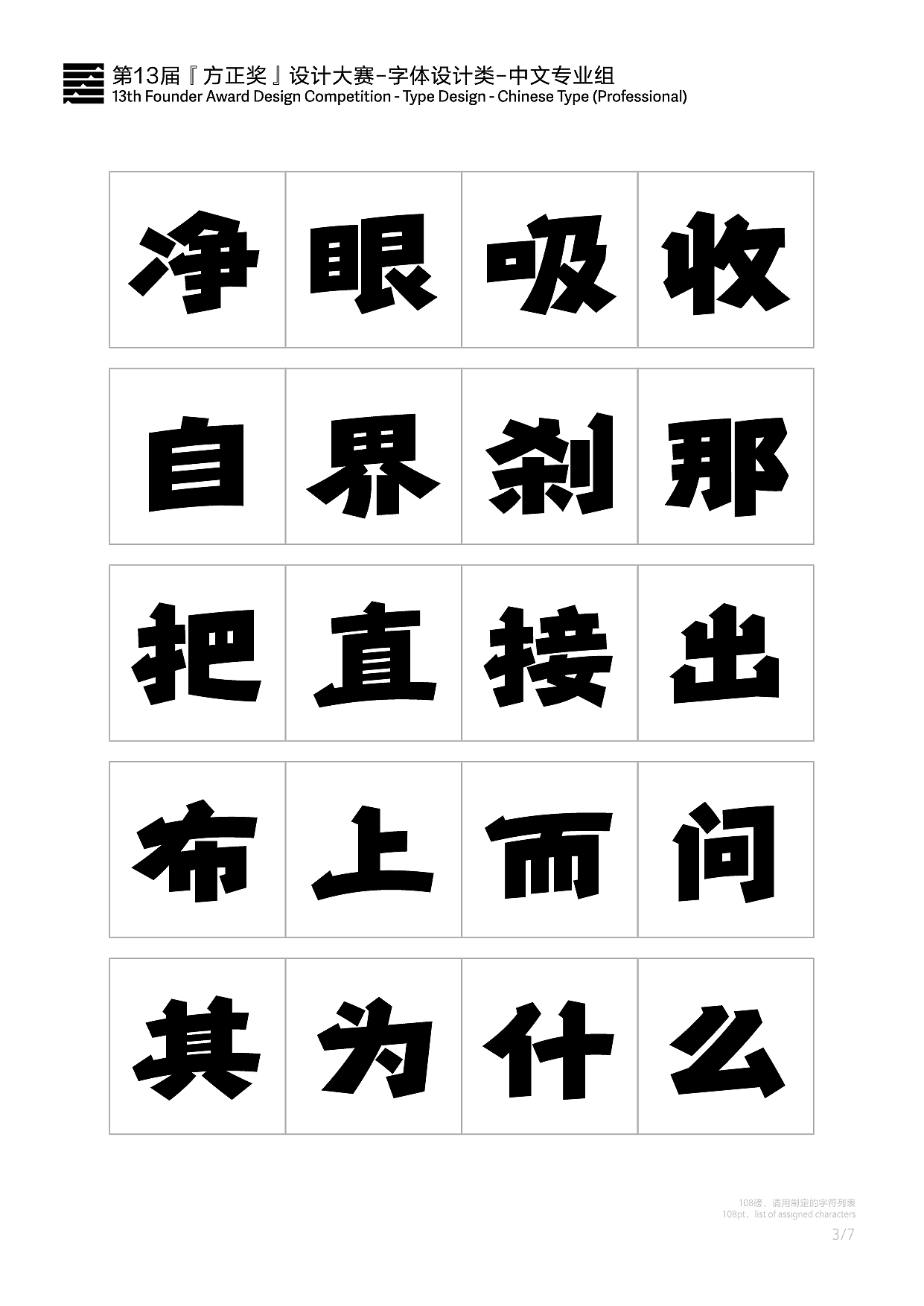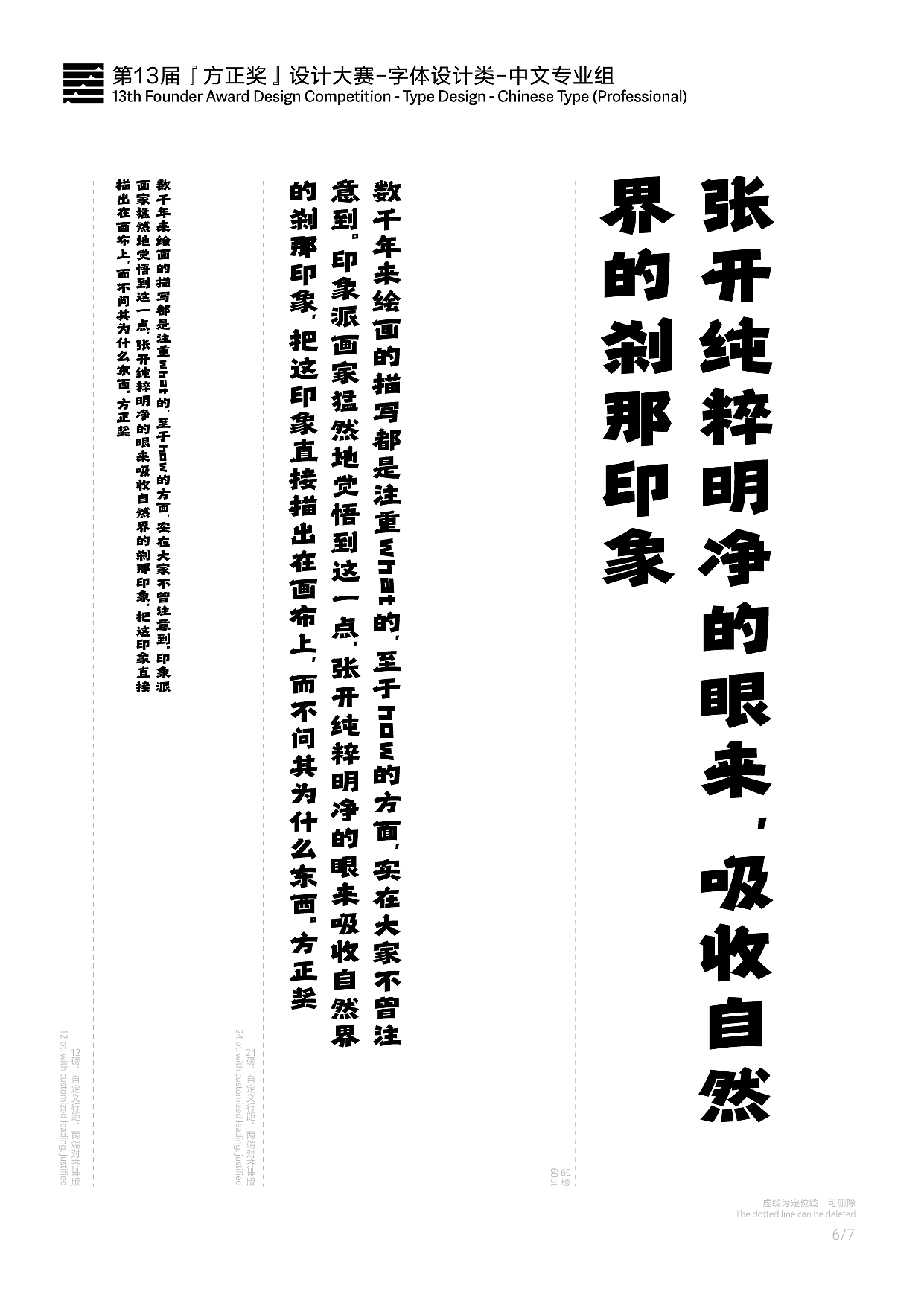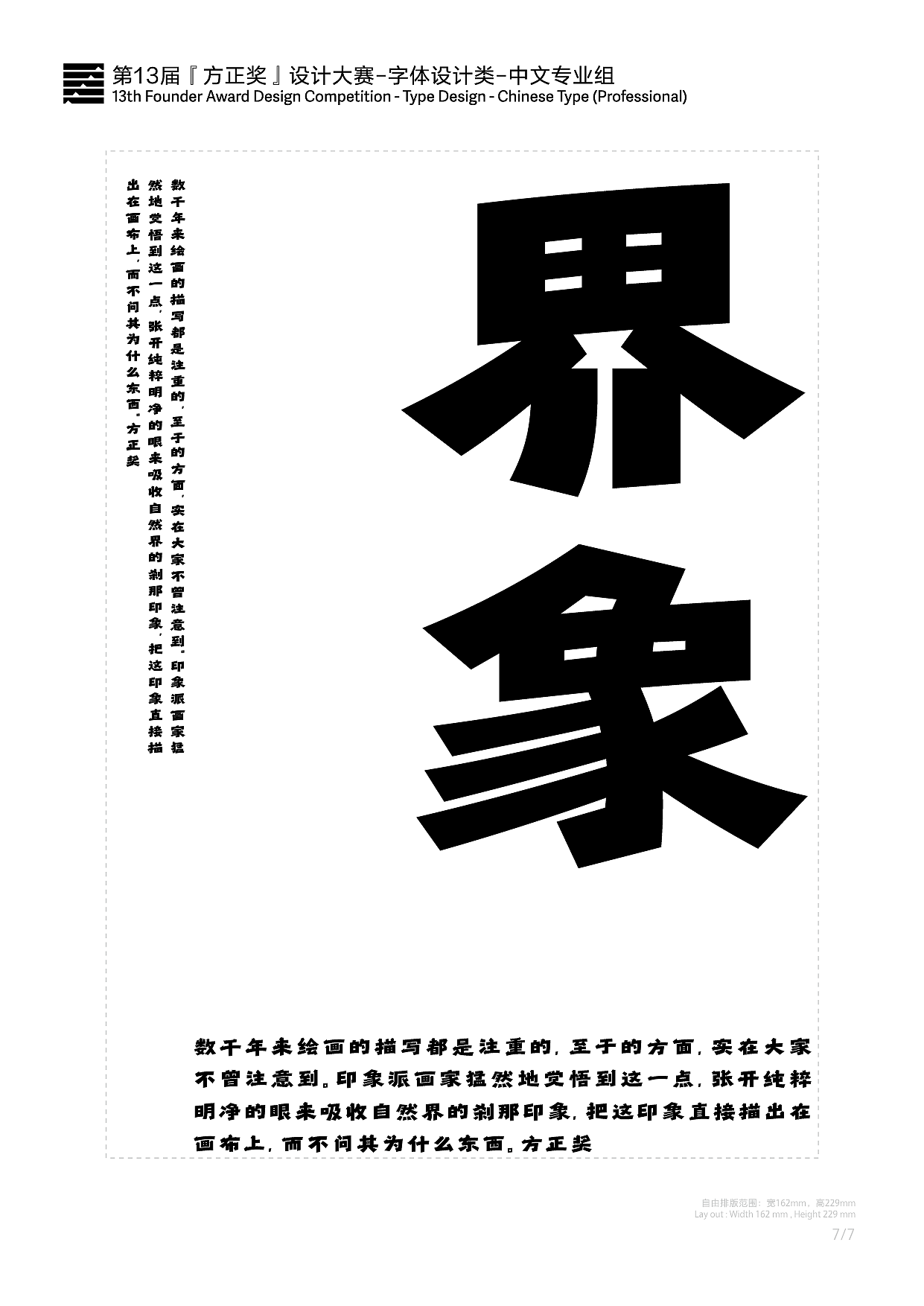
第十三届方正字体设计大赛入围作品-拙象
第一次做字库,很开心能够入围,对目前阶段的我来说,是莫大的鼓励,继续努力!
5704件作品,147件入围,各组金奖空缺,难度逐年递增。如何把字做得又好又有新意,就是下一步的工作了!
文字整体融魏碑之稳笃厚重,合隶书之朴拙灵动,亦映大象沉稳扎实的笃定,稳而不僵;小象跌撞成长的鲜活,拙而有灵。故名「拙象」。
字库设计与书法有所区别,但字体设计的灵感、逻辑还是需要从书法作品中汲取。